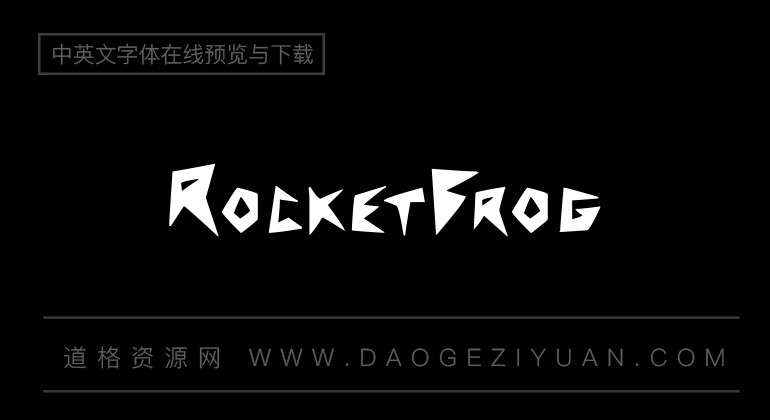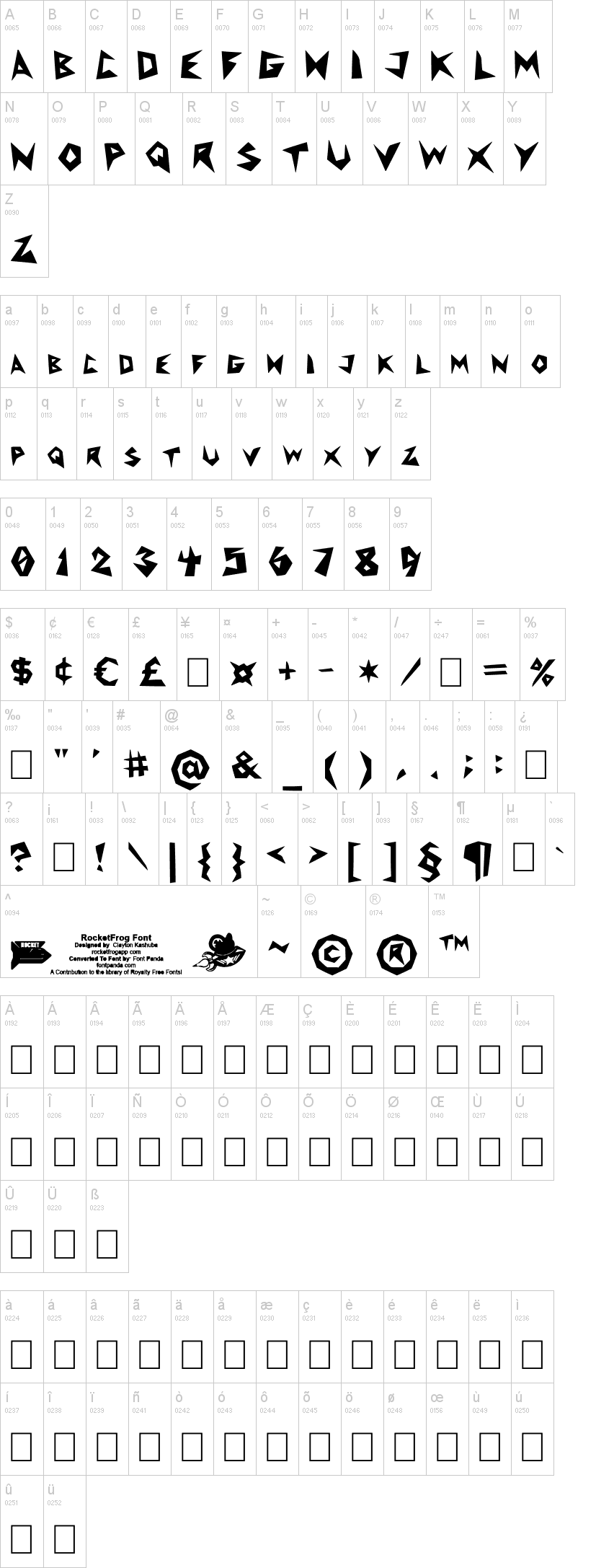
? RocketFrog 字体是一款现代感十足的字体,它采用了大胆的设计,拥有出色的几何结构,可以为你的设计提供更多的可能性。它的字体比例和细节都很出色,能够提供清晰的文本,同时也能为设计带来更多的活力和节奏感。它的设计特点是拥有大胆的几何结构,可以在设计中创造出精致的视觉效果。内容介绍
RocketFrog是一款非常不错的手写艺术字体,具有很好的视觉感,适合于文化类的宣传设计、商业类品牌的广告和产品包装设计以及个性化文字排版等较多场景。